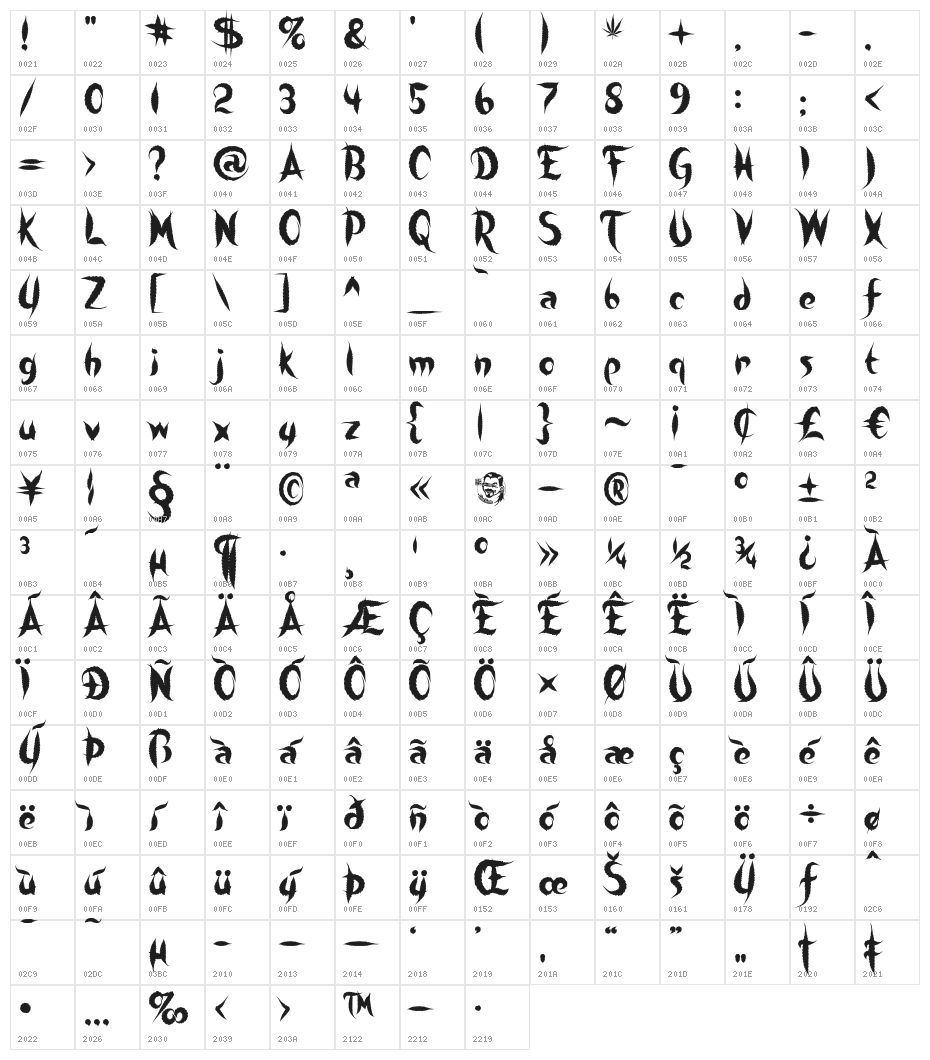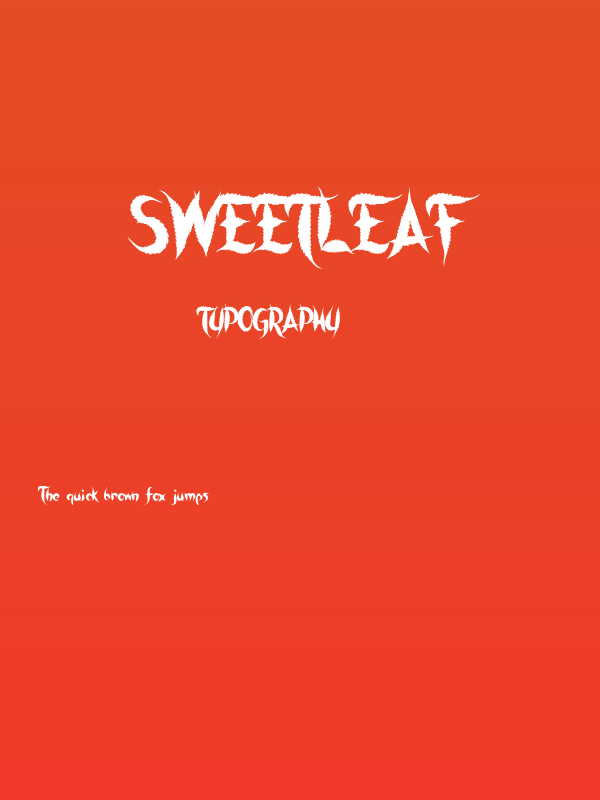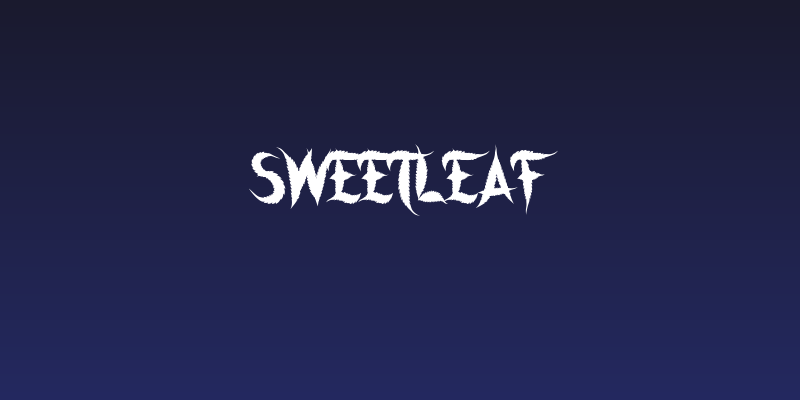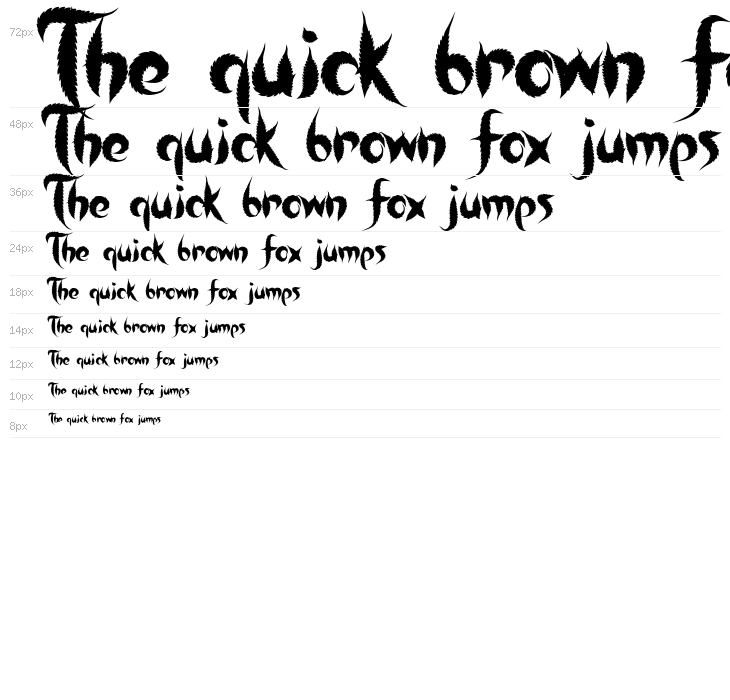
SweetLeaf Font
| Caz de utilizare | Logos, Posters, Headlines |
| Proiecte propuse | Ideal for eco-friendly branding, environmental campaigns, nature-themed posters, and artistic projects requiring a bold statement. |